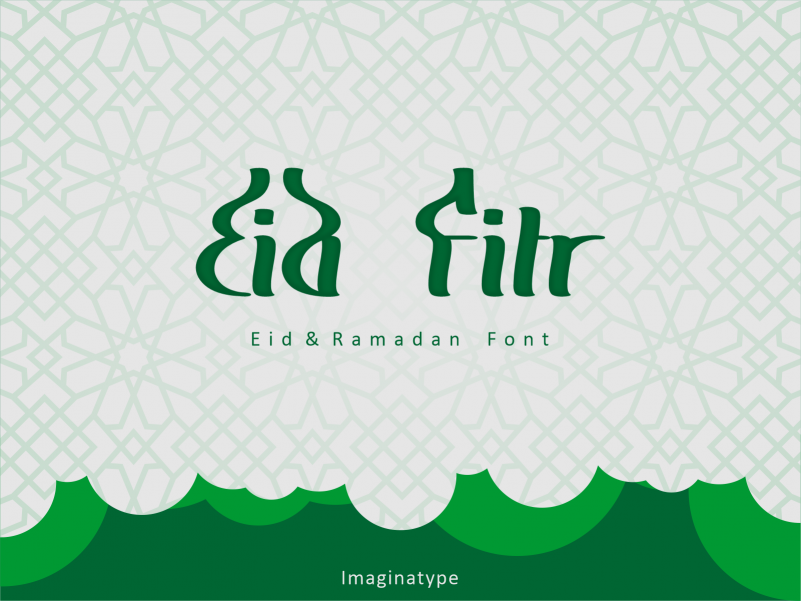
Eid Fitr Font
Esta é uma fonte de display do tipo árabe. Ela possui um estilo elegante, luxuoso e moderno. Aproveite essa fonte para desejar felicidades a seus amigos, família e todos os que você conhece. Ela se adapta perfeitamente a uma ampla gama de projetos gráficos! A descrita font está disponível no formato de display, criada pelo designer Nuryanto Dwi. Seu estilo luxuoso contrasta com o moderno para criar um contraponto elegante e sofisticado que se destaca em qualquer design. Esse não é apenas um recurso visual a ser usado nas suas próximas criações gráficas, mas também uma maneira de expressar seu amor por algo tão especial como uma festa. Descubra o brilho da sua próxima obra com essa fonte de display árabe. Ela se destaca não apenas em um ambiente digital ou impresso, mas também em ambientes físicos e digitais. Nuryanto Dwi criou algo que é tanto uma ferramenta para tornar seus designs únicos quanto uma lembrança do encantamento da festa de Eid Fitr.